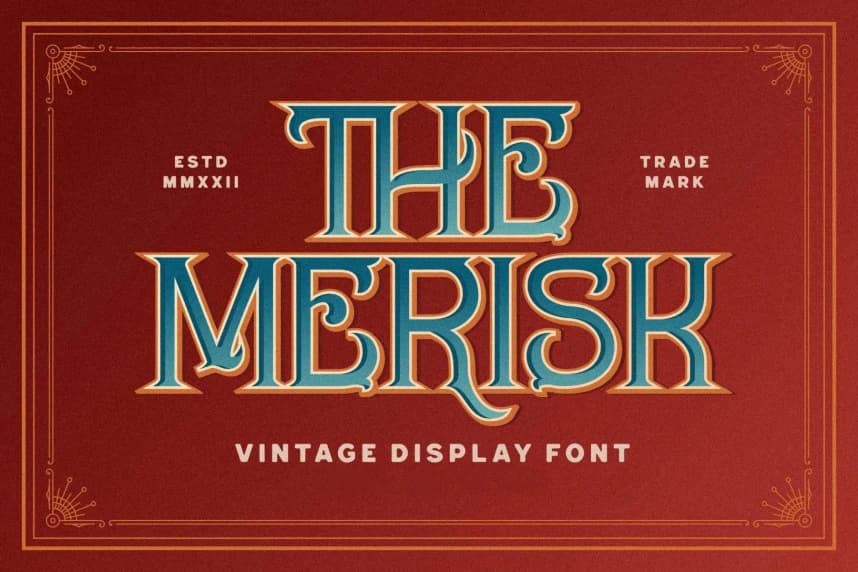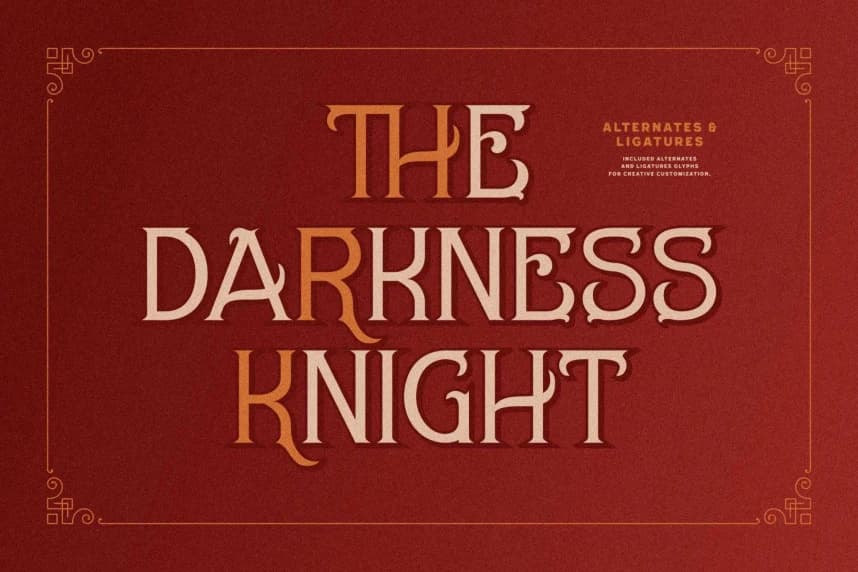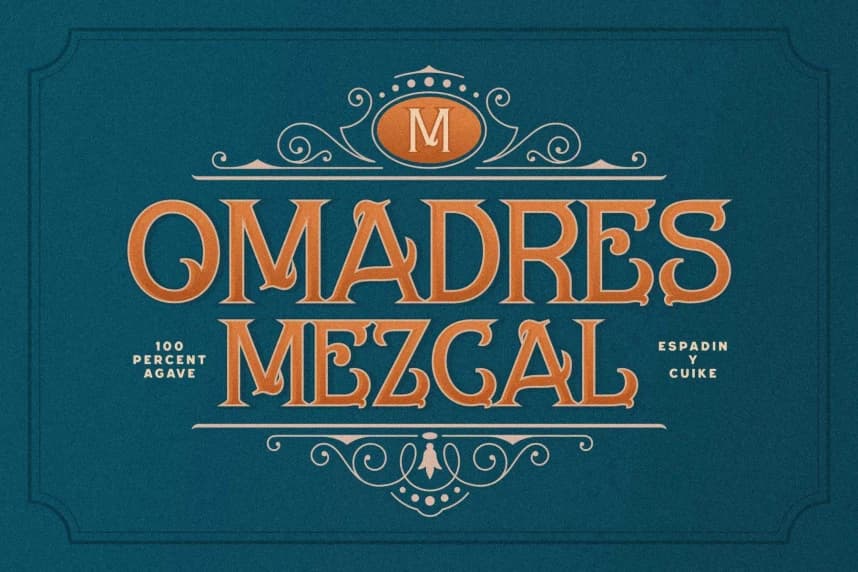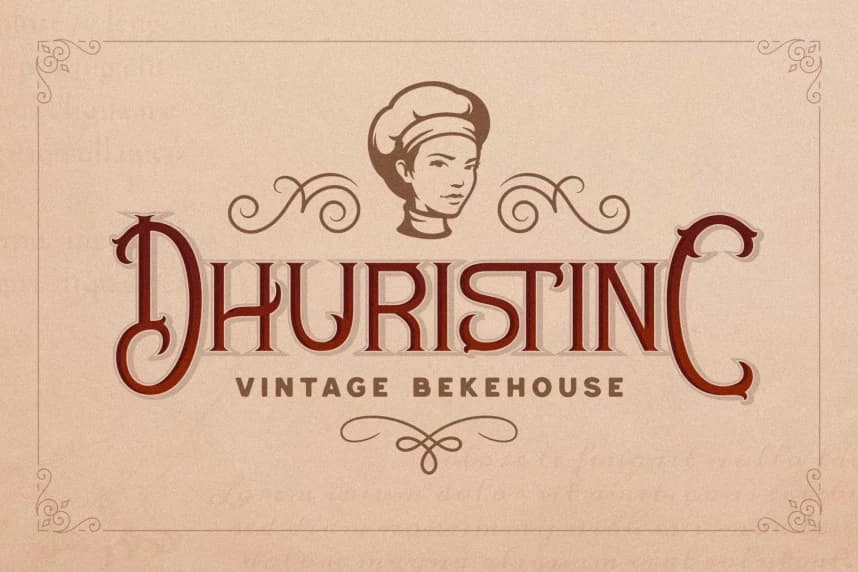
Merisk Font
Merisk Font, belirgin kıvrımları ve vintage cazibesiyle Victorian stilinde süslemeli bir yazı tipidir. İnce ve keskin harf formları, dekoratif derin spiraller ve parantezli serif ile her harfe el işçiliğiyle yapılmış bir görünüm kazandırır ve eczacı tezgahını andıran bir his verir.